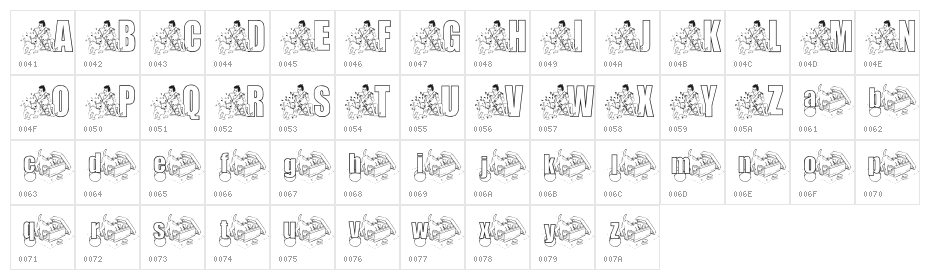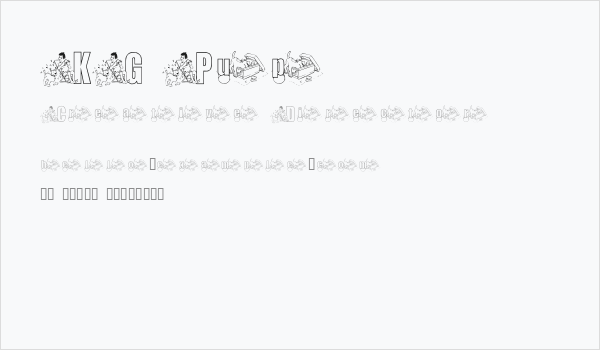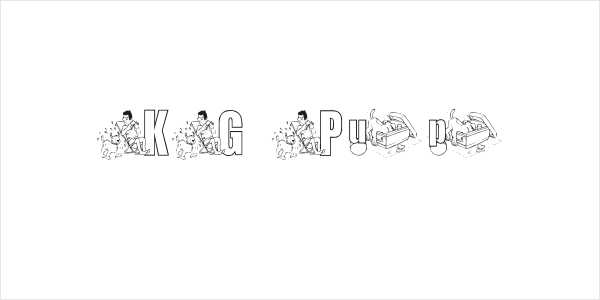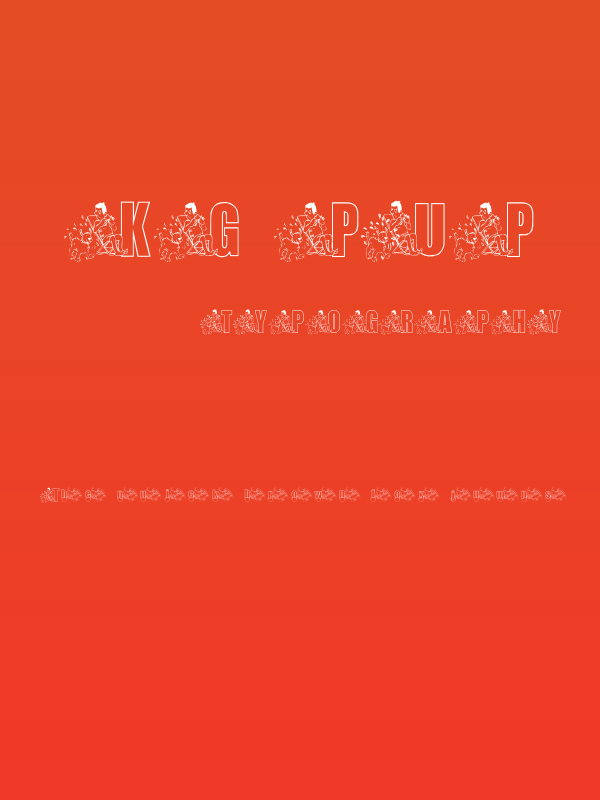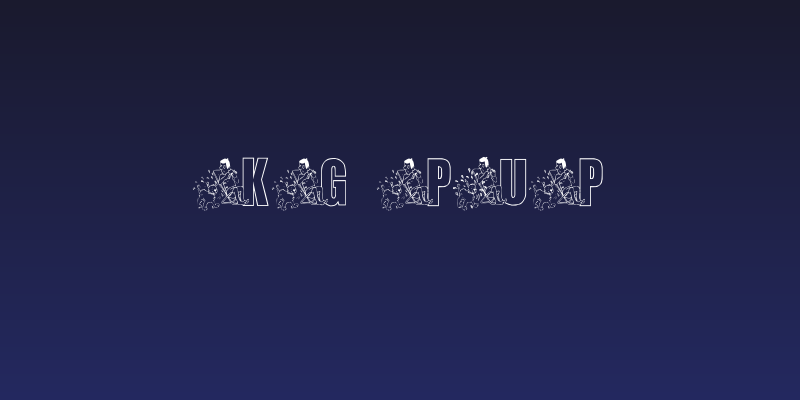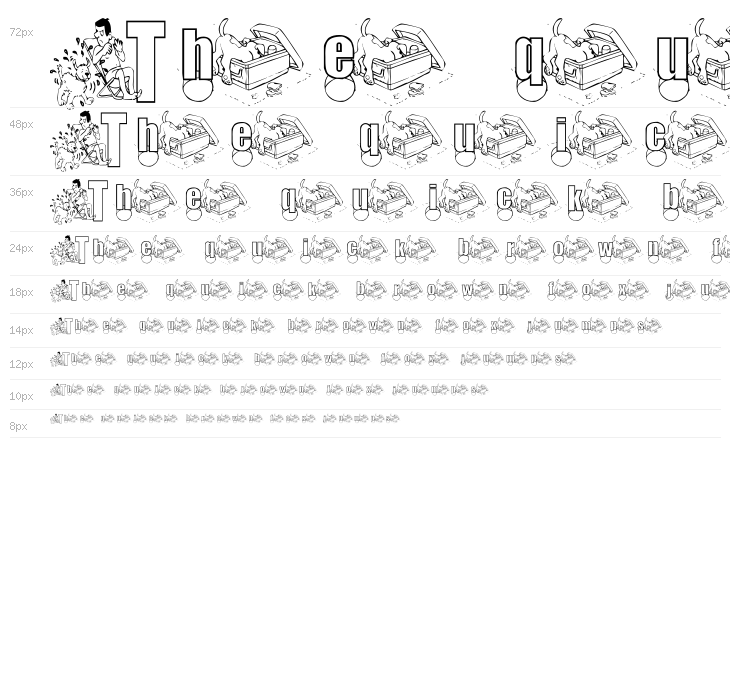
KG Pup Font
KG-PUP MAIUSCOLE
KG-PUP MINUSCOLO
KG-PUP ALTRI CARATTERI
| Stile generale | Playful, Whimsical |
| Caso d'uso | Headlines, Logos, Creative Projects |
| Progetti proposti | Ideal for children's books, pet branding, playful invitations, and educational materials. |